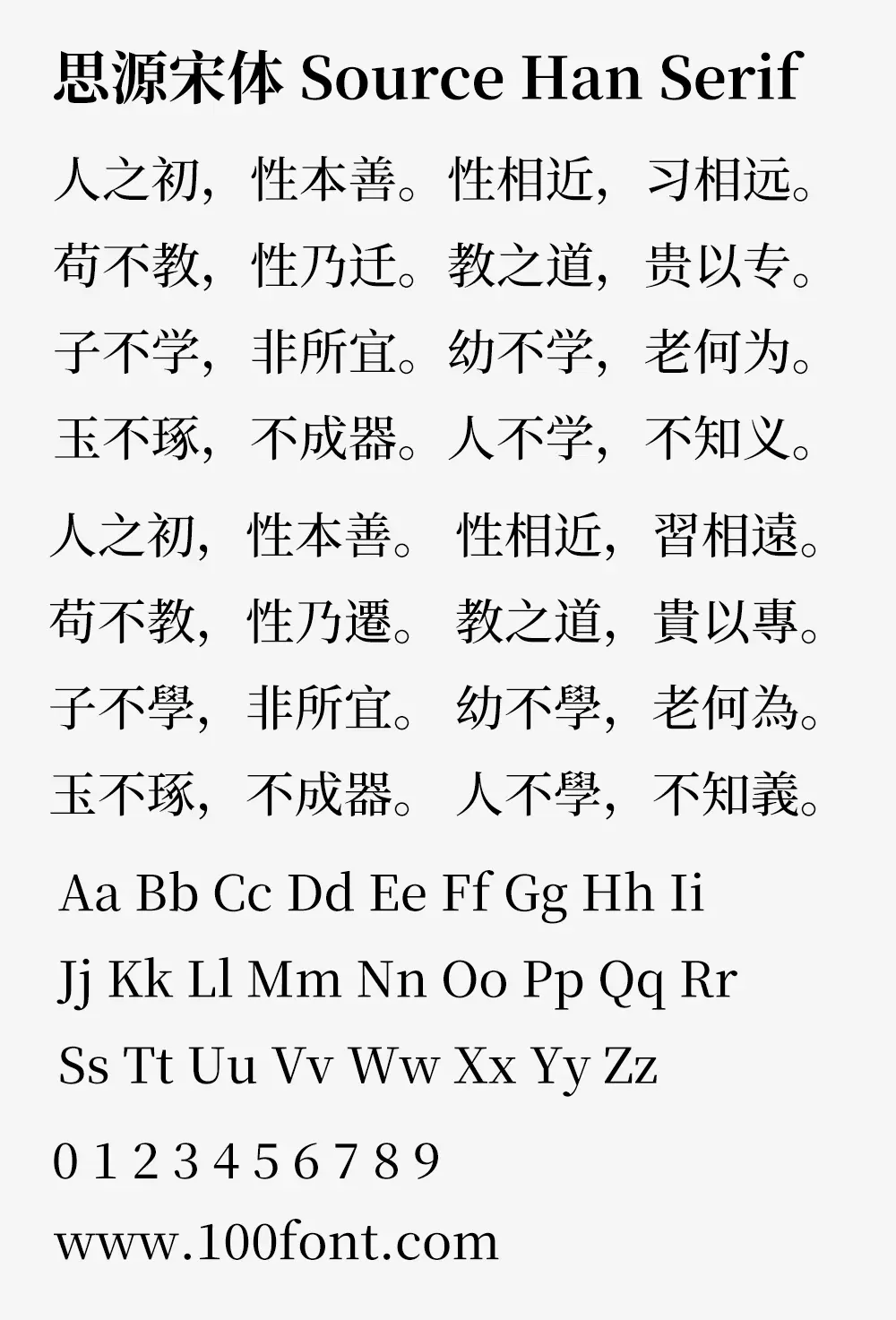
思源宋體(Source Han Serif)是 Adobe 與 Google 合作開發的最新泛 CJK 字體,它是對應於思源黑體的宋體字體。思源宋體與思源黑體這兩種字體是為了響應統一設計的需求,以服務於東亞 15 億人口。
思源宋體支持四種不同的東亞語言(簡體中文、繁體中文、日語和朝鮮語),該字體還包含多個西方字形,支持拉丁語、希臘語和西里爾文腳本,這些字形均來源於 Source Serif。思源宋體總共擁有七種粗細字重,共設計了458745個漢字。也就是說每一種字重包括65535個字形。
思源宋體和思源黑體一樣針對屏幕顯示進行了優化,但思源宋體具有截然不同的風格,適合用於文學性較強的文本或優雅時尚的標題,打印效果也非常優美。